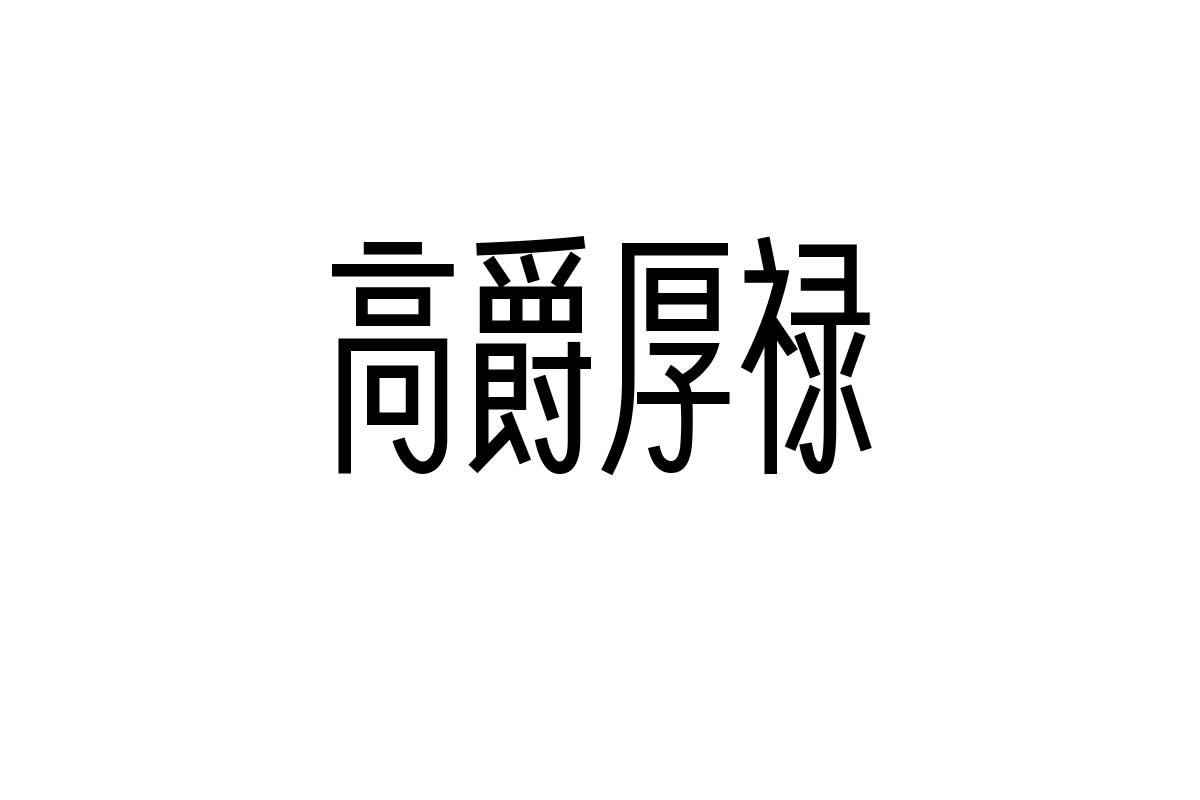
仓耳青雅方体是一款具有现代感和艺术气息的字体,它以其独特的设计风格和优美的字形结构受到了广泛的喜爱。这款字体的特点包括:
1. 简约而不失精致:仓耳青雅方体采用简洁的线条和柔和的曲线,使得整体看起来既时尚又优雅。这种简约风格不仅易于阅读,还给人一种舒适的感觉。
2. 独特而富有艺术感:这款字体的设计灵感来源于中国传统文化元素,如书法、绘画等。它的字形结构独特,既有传统的韵味,又不失现代感。这使得它在视觉上具有很强的吸引力,能够为文字增添一份艺术气息。
3. 适用于多种场景:无论是用于标题、正文还是广告宣传,仓耳青雅方体都能展现出其独特的魅力。它的字形结构紧凑且均衡,适合各种排版需求,使得文字更加醒目和吸引人。
总之,仓耳青雅方体是一款具有现代感、艺术感和实用性的字体,适合用于各种需要展示个性和美感的文字设计中。